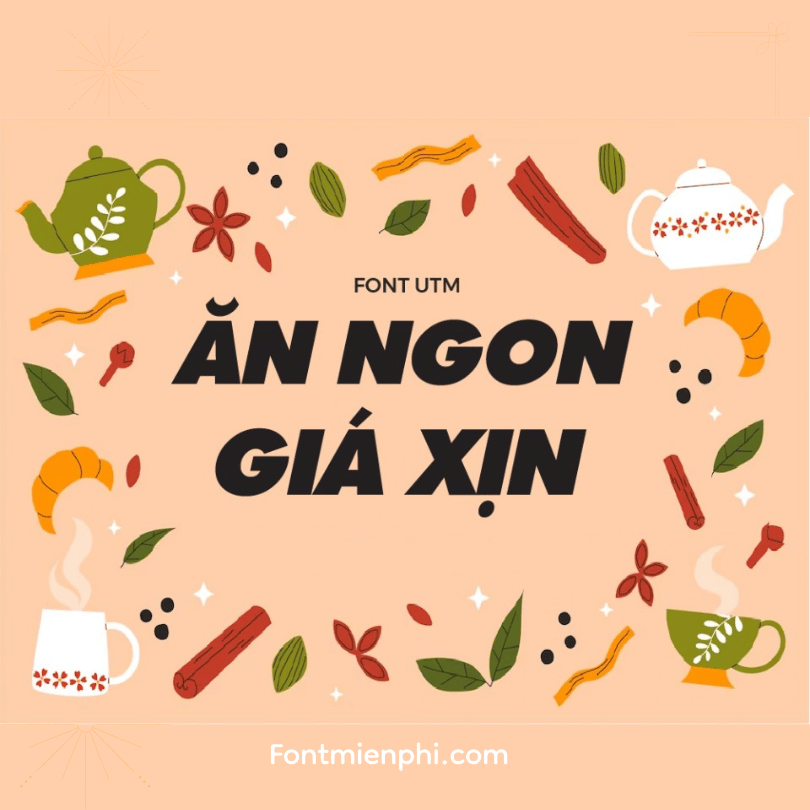
Việt hóa font UTM Sharnay
Hướng Dẫn Việt Hóa Font UTM Sharnay
(Font chữ nghệ thuật sang trọng, phù hợp thiết kế thời trang, logo cao cấp)
1. Kiểm Tra Bản Gốc
• Thử gõ từ “Hà Nội” trong Photoshop/Illustrator
• ✔️ Hiển thị đúng: Đã hỗ trợ tiếng Việt
• ❌ Mất dấu: Cần việt hóa
2. 3 Cách Việt Hóa Hiệu Quả
Tự Chỉnh Sửa (Dành cho designer chuyên nghiệp)
• Phần mềm: FontLab (chính xác nhất) hoặc FontForge (miễn phí)
• Cần thêm:
• Ký tự đặc biệt: đ, ê, ô, ơ, ư
• Cân chỉnh dấu thanh (sắc/huyền/hỏi/ngã/nặng)
Dùng Font Tương Tự
• UTM ThuPhap (cùng họ, hỗ trợ tiếng Việt)
• SVN-Rosemary (phong cách tương tự)
3. Lưu Ý Quan Trọng
⚠️ Chất lượng: Test kỹ ở các kích thước khác nhau
⚠️ Tương thích: Đảm bảo hiển thị tốt trên cả PC/Mac
Mẹo Hay:
• Kết hợp thêm font UTM Avo để phối hợp tiêu đề và nội dung